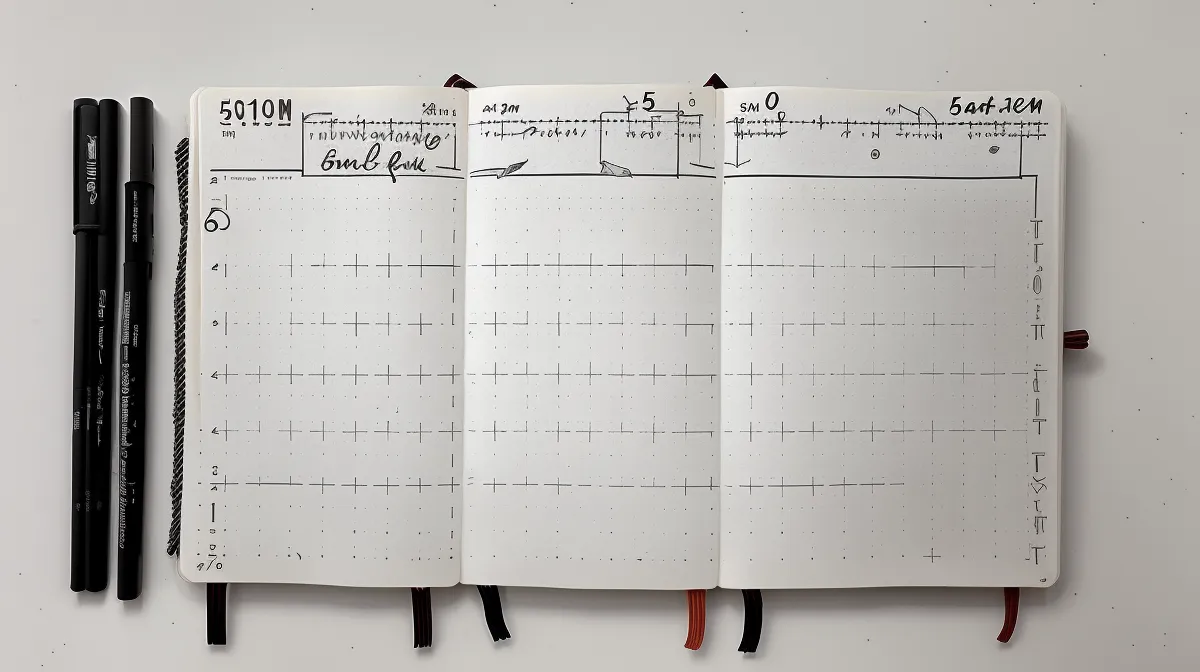
Fünf Millimeter Punktabstand gegen einen randlosen A4-Bogen im Kursvideo: Genau an diesem Unterschied scheitern die meisten Handlettering-Kurse, sobald man sie nicht auf ein Poster, sondern in ein echtes Bullet Journal überträgt. Ein Planer verzeiht keine großzügigen Schwünge, und wer mit den Übungen aus einem normalen Workshop direkt in die Wochenübersicht geht, endet oft mit einem unleserlichen Klecks statt einer sauberen Zeile. Genau dieser Unterschied zwischen Poster-Format und Planer-Format hat mich in einem eigenen, kleinen Kursvergleich monatelang beschäftigt.
Über mehrere Mittagspausen bin ich in der Stadtbücherei Bonn vorbeigegangen, um in Bildbänden nach Beispielen für kleinteiliges Lettering zu suchen, bevor ich die Suche online fortgesetzt habe. Wie unterschiedlich Anfängerkurse aufgebaut sind – manche mit festem Wochenplan, andere als lose Videosammlung ohne roten Faden – habe ich an anderer Stelle ausführlich verglichen; hier ging es mir nur darum, ob ein Kurs überhaupt auf das 5mm-Raster im Bullet Journal eingeht, statt sich ausschließlich auf große Formate zu konzentrieren.
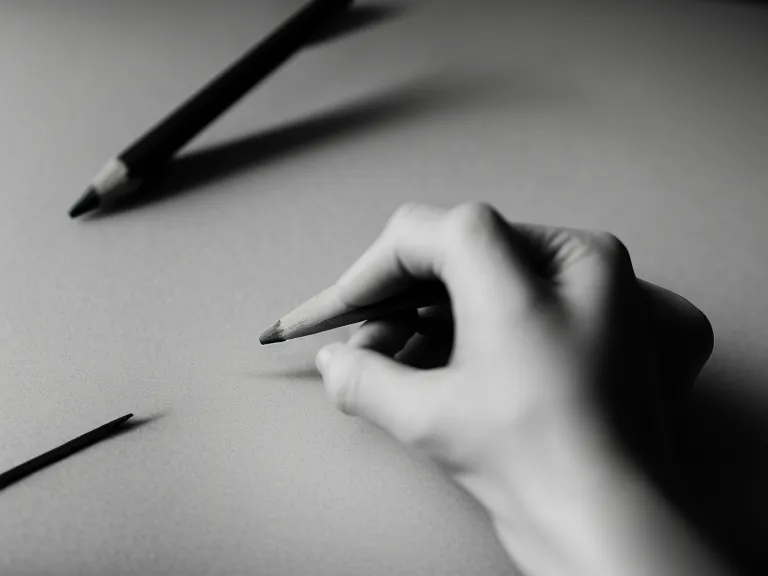
Der Bleistift vor dem Brush Pen
Gegen den Rat vieler Kurse, sofort in einen Brush Pen zu investieren, habe ich meine ersten Wochen nur mit einem einfachen Bleistift geübt. Der Druckaufbau selbst – wann man aufdrückt, wann man die Linie nur hauchzart führt – ist ein eigenes Thema, das ich in einem separaten Kursplan-Artikel Schritt für Schritt durchgespielt habe; für das kleine Raster reicht an dieser Stelle der Hinweis, dass ohnehin nur ein Bruchteil des Drucks nötig ist, den ein A4-Bogen verträgt, und dass zehn Minuten Aufwärmen mit dem Bleistift pro Abend genügen, bevor der Brush Pen überhaupt zum Einsatz kommt.
Samstags übe ich oft zusammen mit Ursula, meiner Kollegin aus der Agentur, die zu diesen Terminen mittlerweile öfter selbstgebackene Kekse mitbringt als dass tatsächlich geschrieben wird. Welche Spitzen dabei wie schnell ausfransen, habe ich in einem eigenen Stifttest gesammelt – für den Planer zählt vor allem, dass eine Spitze überhaupt fein genug für ein 5mm-Feld ist, und nicht jede beworbene Feinspitze hält, was der Name verspricht.
Welches Papier hält dem Bullet-Journal-Raster stand?
Papier entscheidet im Planer oft mehr als der Stift selbst, und ob ein bestimmtes Papier zu einem bestimmten Stift passt, hängt von mehr ab als vom Gewicht allein; die Details dazu habe ich in einem eigenen Papiertest gesammelt. Für meinen Alltag reichte lange die Faustregel, dass zu dünnes Papier durchschlägt und zu glattes Papier dem Stift keinen Widerstand bietet – bevor ich eine ganze Wochenübersicht riskiere, teste ich neue Bögen erst auf ein, zwei Ersatzseiten vorne im Heft. Beim Handlettering Kurs kaufen achte ich seither genau darauf, ob solche praktischen Materialfragen überhaupt behandelt werden, statt nur schöne Alphabete zu zeigen.
Warum der Fineliner im Planer oft gewinnt
Fineliner haben gegenüber dem Brush Pen einen klaren Vorteil für kleine Formate: Mit der Faux Calligraphy lassen sich die dicken Abstriche der Kalligrafie nachträglich als Doppellinie ergänzen, statt sie durch Druck zu erzeugen – wie genau das Schritt für Schritt funktioniert, beschreibe ich in einem eigenen Technik-Artikel. Für den Planer reicht die Erkenntnis, dass man dadurch auch in engen Zeilenabständen präzise bleibt, ohne den Pinselstift zu riskieren.
Andrea Helbig, eine Leserin aus Wuppertal, hatte mir genau deswegen geschrieben, weil sie als Linkshänderin ständig mit der Hand durch die eigene, noch feuchte Zeile wischte. Typisch für sie hat sie sich danach nicht spontan für einen Stift entschieden, sondern erst drei verschiedene Fineliner nebeneinander getestet, bevor sie kaufte. Die Anatomie eines Buchstabens – Oberlänge, Unterlänge, Grundstrich – erkläre ich andernorts ausführlicher; im Kleinformat hilft mir eher das Bild vom Kuchen, den man nicht mehr in großen Stücken schneidet, sondern in Krümeln, wenn jeder Buchstabe nur wenige Millimeter hoch sein darf.
Fünf Wochen, bis der Planer lesbar wurde
Nicht jede Abkürzung spart am Ende Zeit. Einen PDF-Schnellkurs hatte ich mir früh heruntergeladen, in der Annahme, ich könnte die Übungsblätter einfach am Bildschirm durchgehen – ausgedruckt habe ich davon nie eine einzige Seite, und ohne die Blätter auf echtem Papier war das ganze Vorhaben schon nach kurzer Zeit wieder eingeschlafen.
Bis zur fünften Woche hatte sich die Linienführung so weit gefestigt, dass die Wochenübersicht ohne mehrfaches Neuansetzen entstand. Wie viele Abende man realistisch einplanen muss, bis solche Handgriffe sitzen, habe ich in einem eigenen Artikel über Handlettering lernen Dauer zusammengefasst. Als mein Mann in dieser Woche wortlos die frisch beschriftete Geburtstagskarte vom Küchentisch nahm und fragte, wer die geschrieben hätte, wusste ich, dass sich die Übung wirklich ausgezahlt hatte.
Video, PDF oder Procreate für den Planer
Video zeigt Rhythmus und Geschwindigkeit der Stiftführung, ein PDF-Guide eignet sich eher, um Vorlagen unter transparentes Papier zu legen oder als Referenz neben dem Planer liegen zu haben. Für die feinen Details im 5mm-Raster fand ich die Kombination aus beidem hilfreicher als eine einzelne Methode – meist reichen fünfzehn Minuten Video pro Woche, der Rest ist analoges Üben im Heft. Meine ausführlicheren Erfahrungen dazu habe ich im Handlettering Kurs mit Video oder PDF Vergleich festgehalten.
Was am Ende bleibt, ist eine einfache Regel für alle, die Handlettering nicht fürs Poster, sondern für den eigenen Planer lernen wollen: erst das Format wählen, für das man tatsächlich übt, und Kurs, Stifte und Papier danach ausrichten – nicht umgekehrt. Meine Tischdecke trägt inzwischen mehr Tintenflecken, als mir lieb ist, aber die Wochenübersichten sind endlich lesbar, und das war am Ende das eigentliche Ziel.